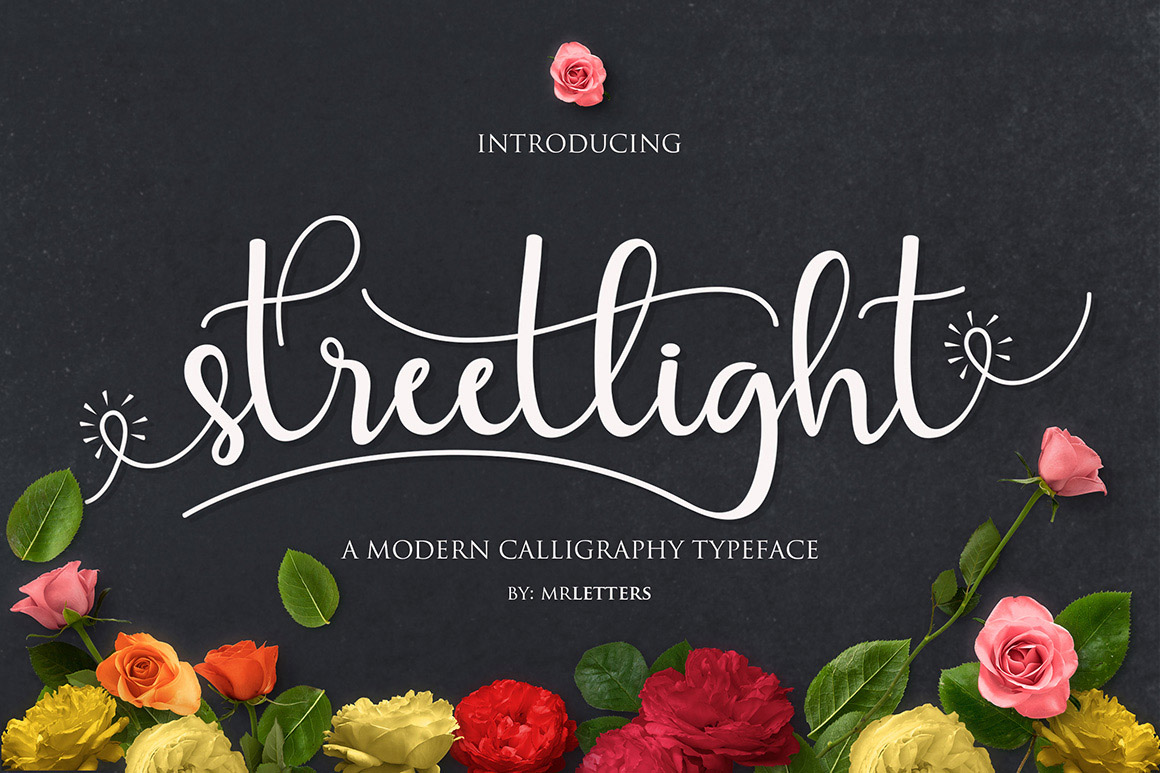
Streetlight
Streetlight: A Fonte Script que Transforma Cada Projeto em Arte
Se você está em busca de uma tipografia que una modernidade e elegância artesanal, a Streetlight Script chega como a escolha perfeita. Criada com traços que lembram caligrafia feita à mão, esta fonte destaca-se em convites de casamento, cartões de aniversário, branding e muito mais.
- Design fresco e contemporâneo – linhas suaves que conferem um toque sofisticado a qualquer peça.
- 459 glifos completos – inclui letras minúsculas, maiúsculas, números, símbolos e ligaduras avançadas.
- Recursos OpenType – recursos como alternâncias contextuais, ligaduras e estilos de conjunto que permitem personalização detalhada.
- Versatilidade de uso – ideal para convites de casamento, cartões de felicitação, identidade visual, cartões de visita, pôsteres e design de embalagens.
- Alta legibilidade mesmo em tamanhos pequenos, graças ao espaçamento bem balanceado.
Por que escolher a Streetlight para seus projetos?
A Streetlight não é apenas uma fonte bonita; ela traz características técnicas que facilitam a vida do designer. As ligaduras automáticas reduzem o tempo de edição, enquanto as alternâncias contextuais garantem que cada palavra tenha um fluxo natural, como se fosse escrita à mão.
Aplicações Ideais
- Convites de casamento – cria uma atmosfera romântica e exclusiva.
- Cartões de aniversário – adiciona um toque festivo e personalizado.
- Branding & identidade visual – fortalece a imagem de marcas que buscam sofisticação.
- Pôsteres e flyers – destaca títulos e chamadas de forma impactante.
- Materiais corporativos – cartões de visita e papéis timbrados ganham elegância instantânea.
Com sua estética artesanal combinada à potência dos recursos OpenType, a Streetlight Script se destaca como a fonte preferida para designers que desejam imprimir personalidade e classe em cada detalhe. Seja para projetos pessoais ou corporativos, esta tipografia oferece a flexibilidade e o charme necessários para transformar sua comunicação visual.